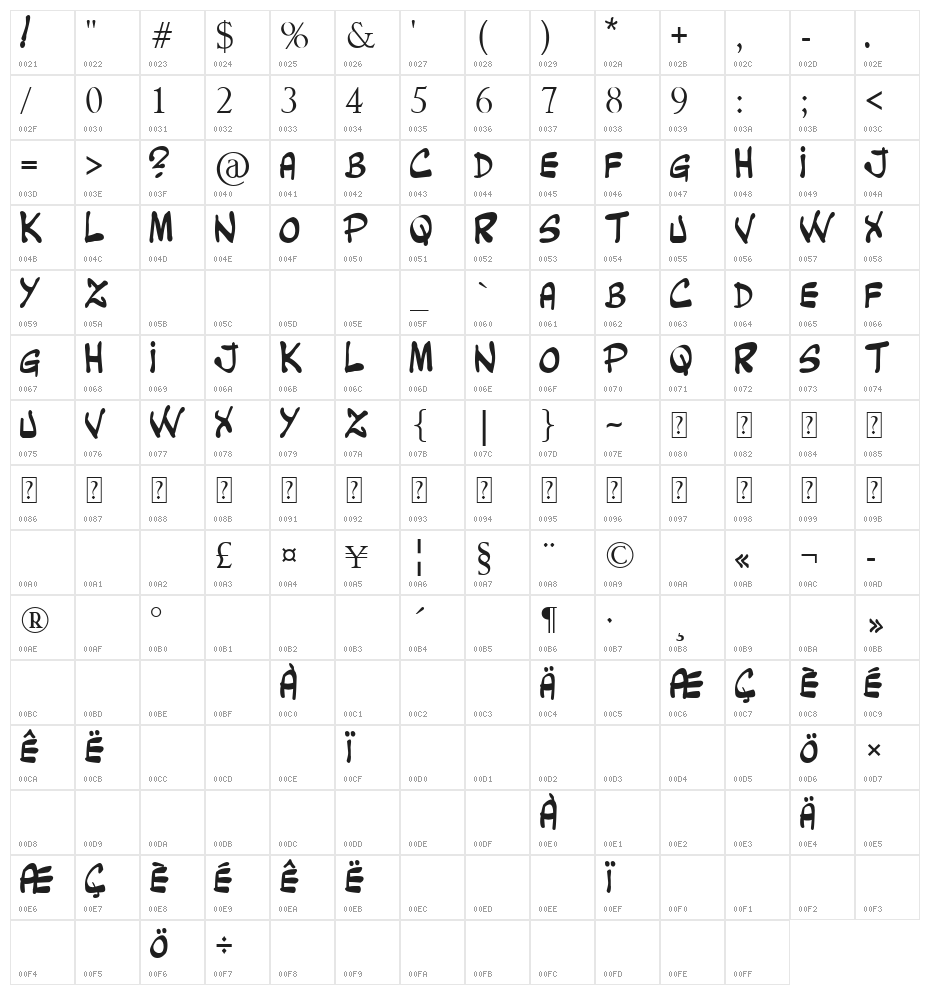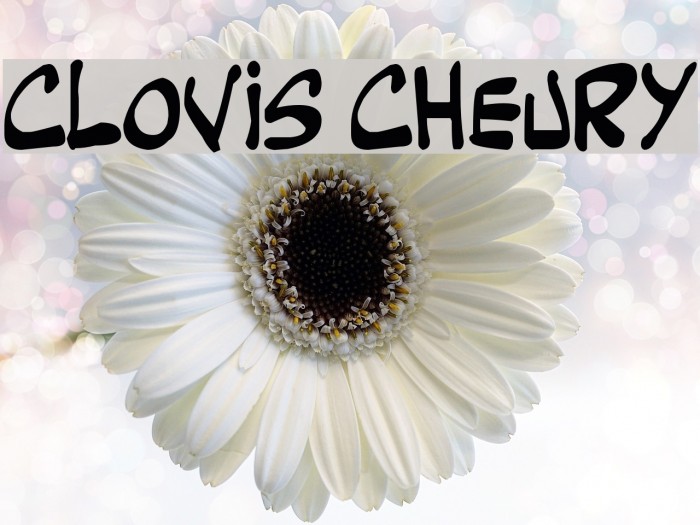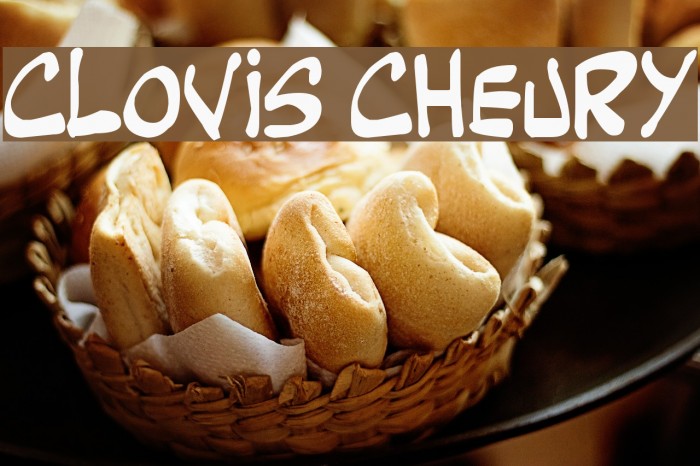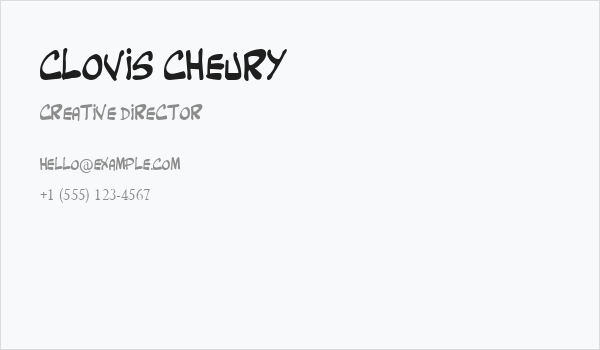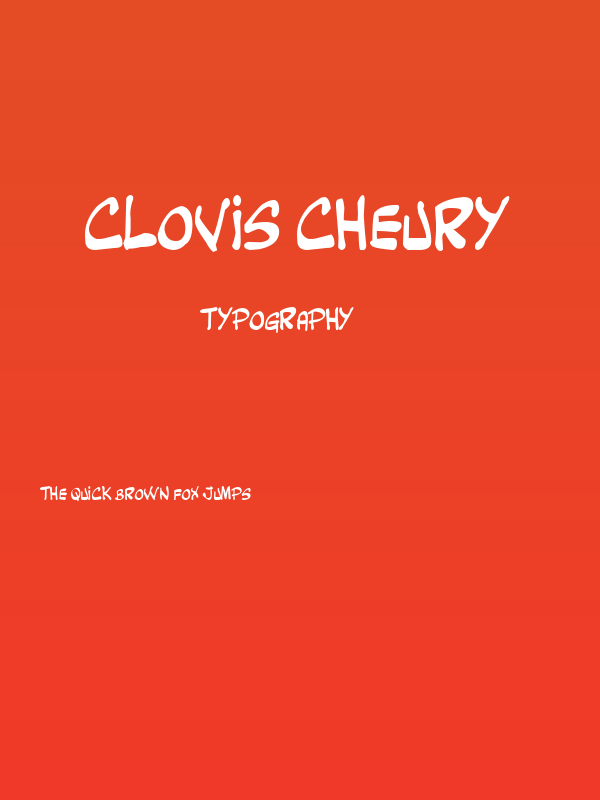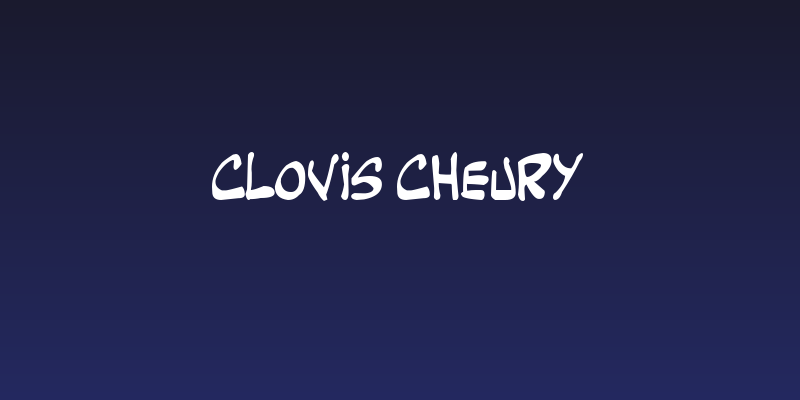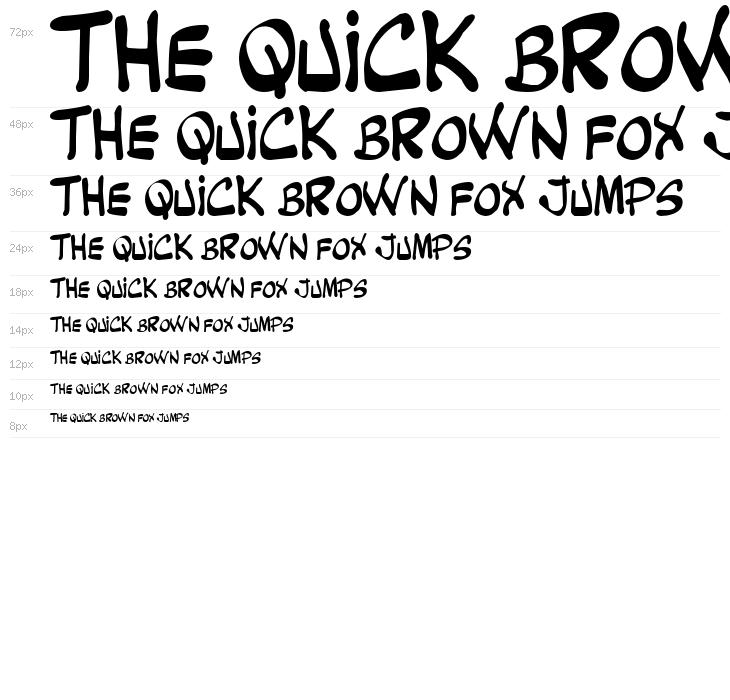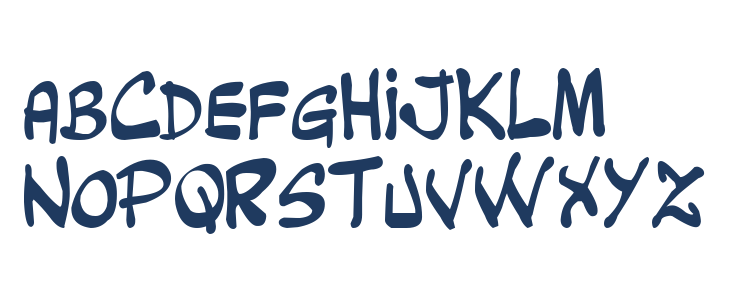
clovis cheury Font
| Gesamtstil | Playful |
| Anwendungsfall | Headlines, Logos, Creative projects |
| Vorgeschlagene Projekte | Ideal for greeting cards, children's books, playful branding, and creative posters. |